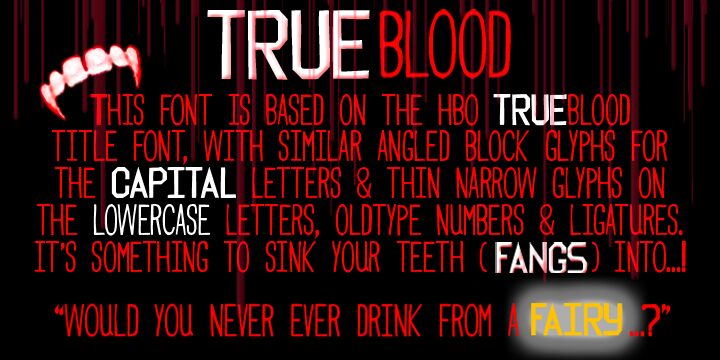
Dies ist meine eigene Version der TRUE BLADE- und TRUE GOTHIC-Schriften, die in der Serie TRUEblood verwendet wurden. Sie wurde akribisch anhand zahlreicher Screenshots und mit viel künstlerischem Geschick erstellt. Wenn du das O mit dem Unterstrich möchtest, verwende das Komma (,).
TRUEblood